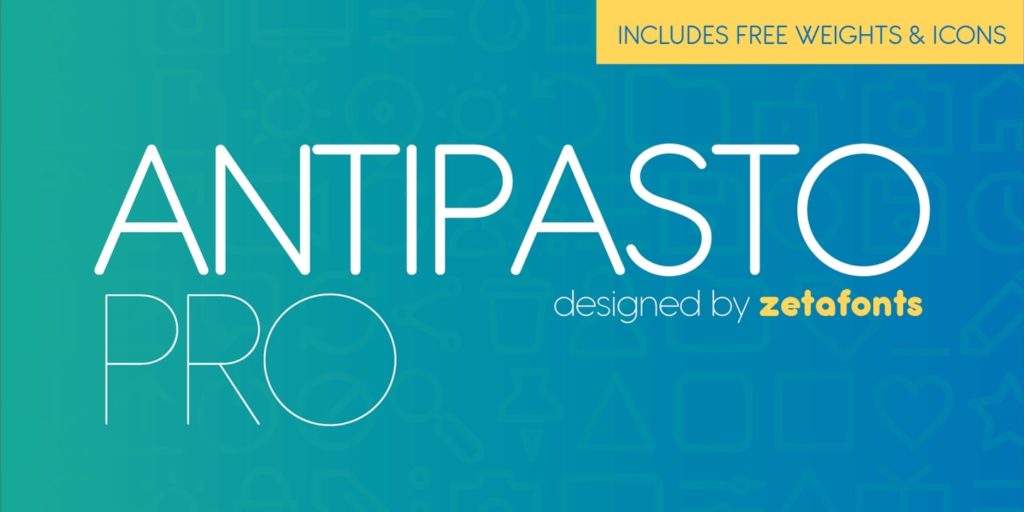
Шрифт Antipasto Pro
это округлый геометрический гротеск от студии Zetafonts и дизайнера Козимо Лоренцо Панчини, выпущенный в обновлённой версии в 2017 году. В отличие от оригинала, версия Pro значительно расширена: добавлены кириллические и греческие символы, а также набор иконок. Шрифт отличается мягкими формами букв с характерными скруглениями, что придаёт ему дружелюбный и современный вид. Он идеально подходит для заголовков, логотипов, брендинга и современной вёрстки, где требуется сочетание геометрической чистоты и тёплой атмосферы. Скачать бесплатно можно для некоммерческих проектов, соблюдая условия лицензии CC BY-NC